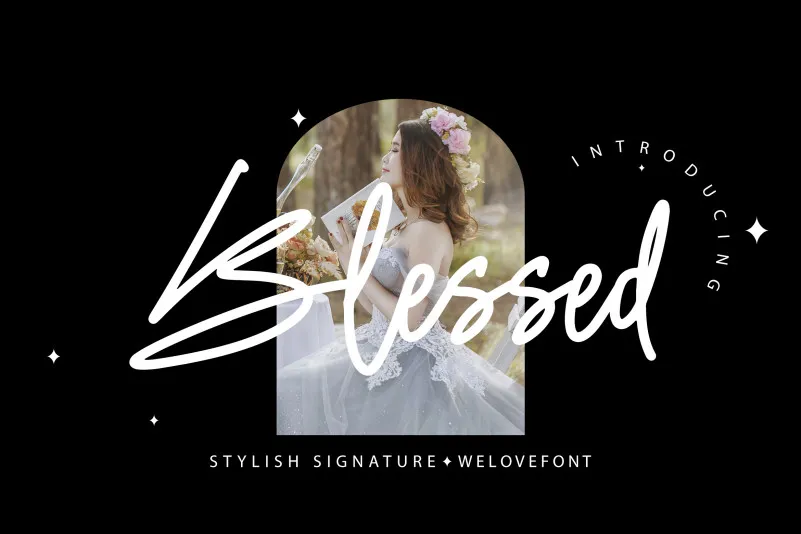
Blessed Font – Download Grátis
A “Blessed Font” é uma elegante fuçinha que traz com ela estilo refinado e vibe moderna. Composto por linhas leves e estilizadas, essa fonte escrita a mão certamente será um complemento perfeito para qualquer projeto criativo. Seja em design de logos, ilustrações ou até mesmo em textos legíveis, o “Blessed Font” garante um toque sofisticado e moderno sem perder sua versatilidade na execução. Ideal tanto para ambientes profissionais quanto para expressões artísticas pessoais, é uma excelente escolha para quem valoriza a qualidade no design de fontes. Se você está procurando por algo que dê vida à sua criatividade enquanto mantém os detalhes essenciais do seu projeto, o “Blessed Font” certamente faz parte da lista.